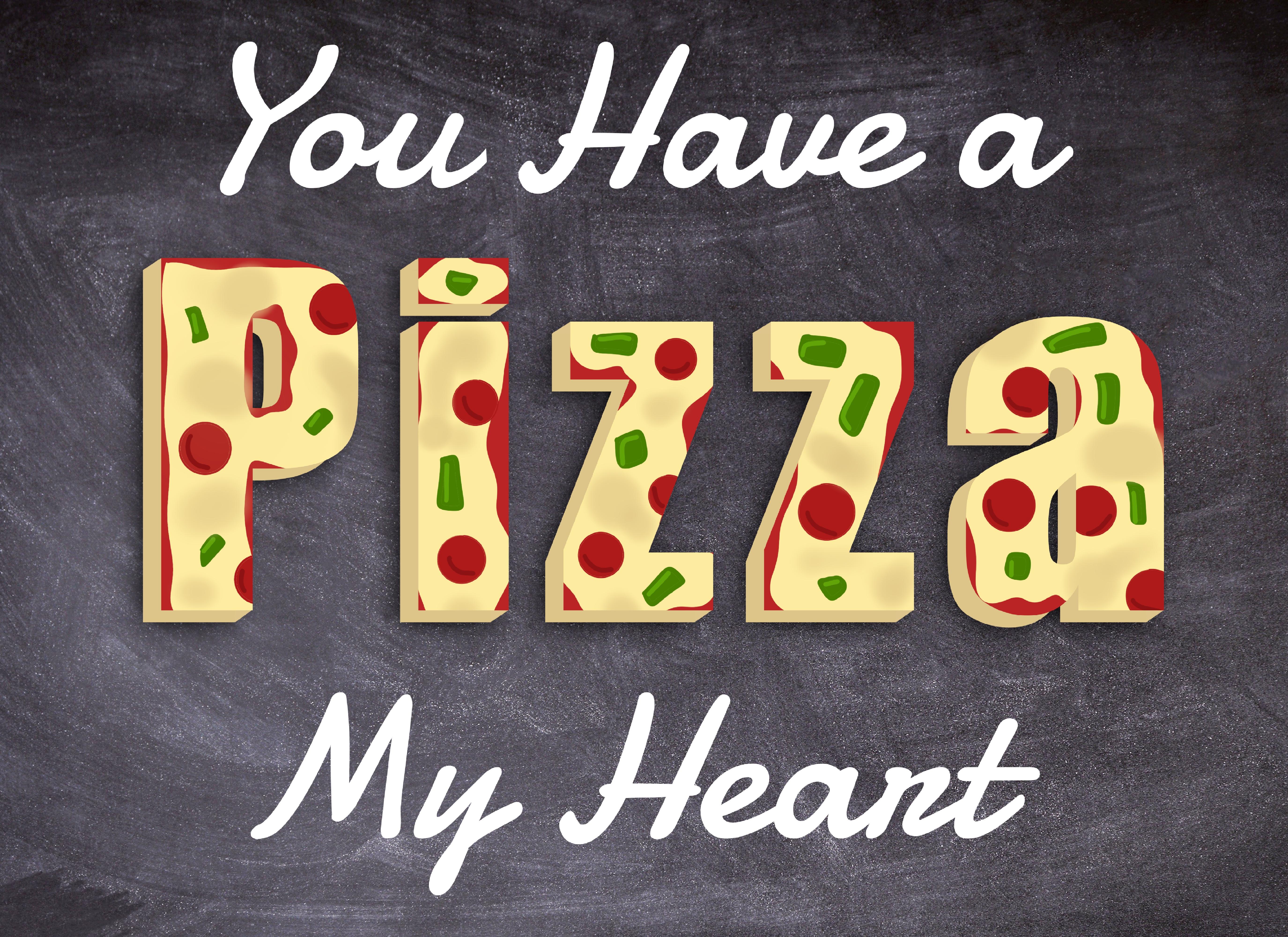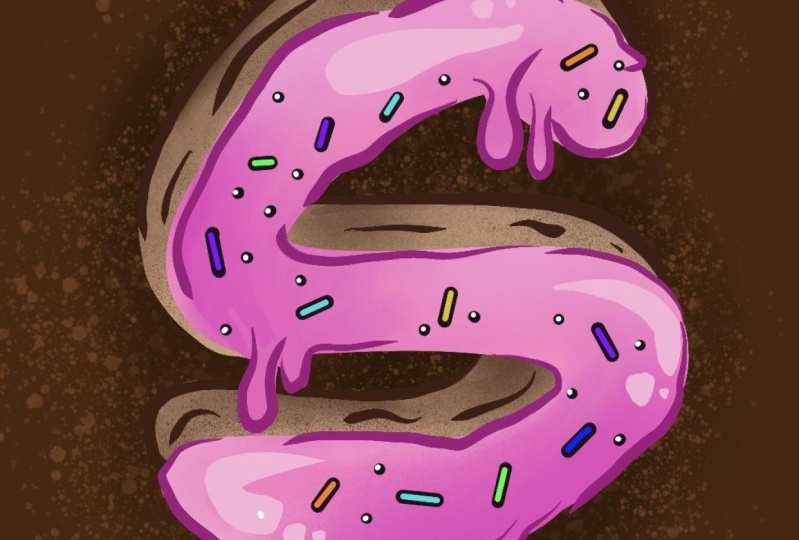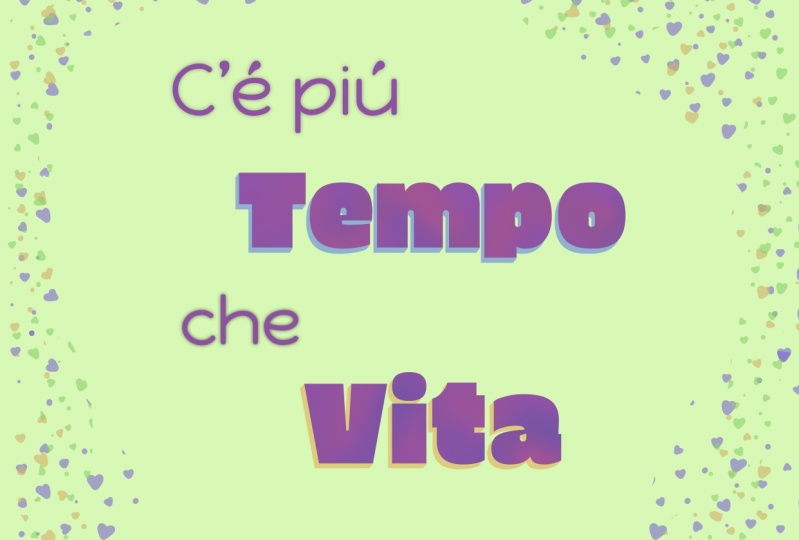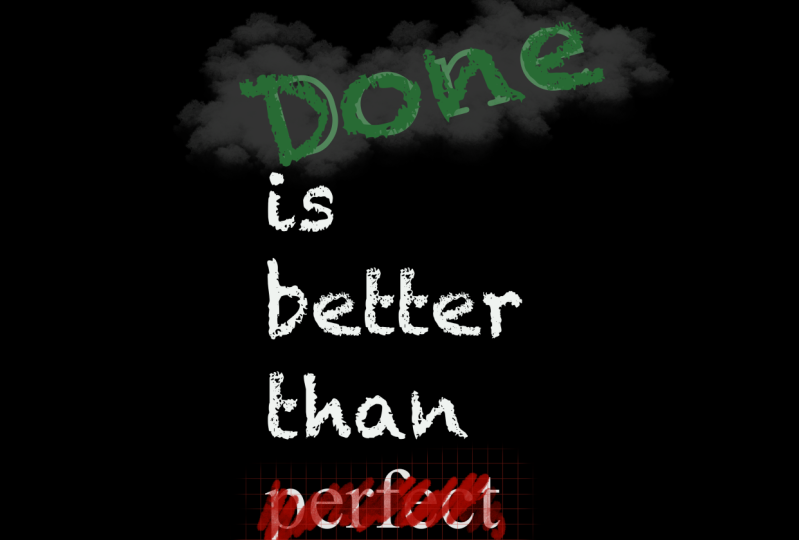
Level sua tipografia com escovas de criação | Danielle Brunner | Skillshare
Level sua tipografia com escovas de criação
Este curso combina o design gráfico com técnicas ilustrativas para aprimorar sua tipografia. Você vai aprender a usar escovas em texto para criar uma imagem dinâmica que pode ser usada em cartões de aniversário, cartazes/impressões de arte, posts de mídia social e muito mais! Não são necessárias habilidades de letras de mão!
E como bônus, você também vai aprender a criar sua própria escova de criação de criação. Esta aula é ótima para aqueles novos em Procreate, design e ilustração digital.
1. 1 classe de tipografia Introdução 10: Você já quis explorar mais do que apenas ilustrar e desenhar no Procreate no seu iPad? Bem, neste curso, eu vou te mostrar exatamente como fazer isso. Olá, meu nome é Danielle Burner. Sou designer gráfico e ilustrador de Pittsburgh, Pensilvânia. Neste curso, mostrarei as ferramentas e truques necessários para melhorar sua tipografia e procriar. Vamos criar um projeto divertido com tema de sobremesas. E depois de concluir sua arte, você pode usar o que aprendeu para criar seu próprio tema para digitar quatro pôsteres, cartões de aniversário, postagens nas redes sociais e muito mais. E, como bônus, mostrarei como criar o pincel para confeitos para doces que incluí para você neste curso. Vamos começar. 2. 2 recursos de downloads de recursos de introdução de recursos: Estou muito animada para começar esta aula focada em meus dois assuntos favoritos, arte e deserto. Mas antes de começarmos, você vai querer baixar os recursos que eu forneci para você na seção de projetos e recursos abaixo deste vídeo. Verifique se você está usando o site da Skillshare e não o aplicativo para acessar esses arquivos. Você fará o download do arquivo de topografia do deserto dos pincéis e do arquivo de cores da paleta do deserto. Ao clicar neles, sempre escolha a opção abrir e procriar. Em seguida, você encontrará o novo conjunto de pincéis na parte superior da sua biblioteca de pincéis e a paleta de cores será adicionada à sua biblioteca de amostras. Por fim, quero mostrar como acessar as duas fontes gratuitas que usaremos nesta aula. Acesse fonts.google.com, LinkedIn, a seção Sobre abaixo deste vídeo. Aqui, você pesquisará e baixará happy monkey e Erica, um. Se você quiser escolher seu próprio tipo de letra ou usar os que você já tem, certifique-se de usar duas opções de contraste. Um tipo de bloco san-serif mais espesso e outro com uma escrita ou um peso geral mais leve. Você pode usar as propriedades da fonte para restringir suas pesquisas em fonts.google.com. Agora que você tem todos os seus recursos, estamos prontos para começar a criar nossa tela. 3. 3 preparo e layout de fontes do Canvas: Nosso primeiro passo será criar nossa tela e preparar nossas fontes. Abra seu aplicativo Procreate e criaremos um novo Canvas. Então, você tocará no sinal de mais no canto superior direito. E vamos usar uma tela de 4.000 por 4.000 pixels. Isso é algo que eu já criei, mas se você não tiver isso em sua biblioteca anterior do Canvas, mas se você não tiver isso em sua biblioteca anterior do Canvas, toque neste sinal de adição aqui e verifique se ele está configurado para pixels. Você pode ver que aqui suas opções estão desse lado. Então, vamos digitar 4.000,4 mil. E você verá que se estivermos em 300 DPI ou as camadas máximas forem 29. Então, podemos ter 29 camadas nesta peça. Se você aumentar o tamanho , as camadas diminuirão. Então, preste atenção a isso quando estiver fazendo qualquer projeto. Toque em Criar e a tela em branco estará pronta para ser usada. Próximo. Vamos adicionar nossa cor de fundo. Então vá para o menu Camadas e selecione a cor de fundo. Com a paleta do deserto carregada. Vou selecionar esse tom azul escuro. Agora, vamos adicionar nosso texto. Vá até o ícone da chave inglesa, que é o menu Ações. Verifique se você selecionou adicionar e adicionar texto. Vamos começar com a palavra doce. Toque duas vezes e selecione a seleção da fonte. Já tomei Erica Won. Mas se você estiver em outra coisa, certifique-se de ir até Erica won ou bloquear o texto que você escolheu e clicar em Concluído. Selecione a seta para redimensionar. Você pode selecionar Snapping se quiser que ele fique exatamente no meio. E ele se encaixará no local que você deseja. Para torná-lo mais exato. Você verá que a Suíte foi adicionada à sua própria camada aqui. Vamos adicionar mais um pouco de texto. Então, primeiro vamos ter uma e eu quero mudar essa fonte para a fonte Happy Monkey que escolhemos. Está feito. Eu faço isso um pouco menor. Vou fazer doces ainda maiores. Centralize isso. E vamos adicionar a parte inferior, que vai dizer aniversário. Você pode selecionar todas as três camadas de textos certificando-se de que estejam todas selecionadas aqui, aniversário. E então vamos deslizar para a direita. Deslize para a direita novamente e você verá que todos os três estão destacados. Você pode ir até a seta e mover todas elas ao mesmo tempo depois de ter tudo configurado. Dessa forma, se você estiver ativada, você pode colocar tudo no centro. Ok, isso parece muito bom. Então, em seguida, vamos começar a desenhar para aprimorar a palavra doce e transformá-la em um deserto. 4. 4 dicas para adicionar profundidade: Em seguida, usaremos algumas habilidades de desenho para criar nossas próprias letras em bloco em 3D. Vamos começar aqui, certificando-nos de que nossas fontes são e da cor em que queremos que elas estejam. Os meus já estão prontos. Mas você verá que esse é o rosa escuro que eu escolhi como a cor da cobertura. Se você não estiver nessa cor, você pode tocar duas vezes na fonte que deseja alterar, para selecioná-la, tocar na sua cor e alterá-la. O que vamos fazer agora é garantir que a fonte doce seja selecionada. Deslize para a esquerda e duplique. Selecione a cor doce inferior e toque em. Vamos colocá-lo em restaurantes. Isso permitirá que você faça alterações na decoração, mas não poderá alterar o tipo. Portanto, certifique-se de que, depois de rasterizar, você já definiu a palavra como, você queria dizer. Agora vamos escolher o Alpha Lock. E você verá esse fundo quadriculado. É assim que você sabe que o Alpha Lock está ligado. Isso nos permitirá mudar apenas essa palavra, exatamente o que está selecionado aqui. Vamos escolher a cor do biscoito. Toque nessa camada inferior doce que está na camada de preenchimento de bloqueio alfa. E agora você pode ver que mudou para essa cor de dez biscoitos, o que é uma maneira muito fácil de fazer isso. Toque e retire-o do Alpha Lock. Você não deve mover a ferramenta e nós vamos mover isso. Na verdade, vou tirar a foto. E vamos apenas movê-lo um pouco para dar um efeito 3D. Estou movendo-o para baixo e para a esquerda um pouco. E agora estamos prontos para começar a preencher com nossas ferramentas de caneta. Quero que você acesse o menu Camadas e crie uma camada abaixo da camada Sweet. Então, você tocará nesse sinal de mais e ele o colocará automaticamente acima. Então, basta pegá-lo e arrastá-lo para baixo. Aqui. Vamos usar o conjunto de canetas para topografia do deserto. E vamos usar a caneta técnica porque ela é menor e mais fácil para detalhes finos. E certificando-se de que você está na nova camada abaixo. zoom e adicionaremos algumas linhas para criar letras em bloco. Então você vai querer desenhar. E se você segurar sua caneta verá que ela forma uma linha reta. E você deve preenchê-lo para poder colorir até o fim ou garantir que tenha uma forma sólida preenchendo os três lados. Você vai ver se tiramos isso e tiramos isso. Eu fiz um triângulo. É assim que você sabe que o preencheu. E então você pode usar a cor solta ao tocar e segurar e arrastar e soltar para preencher a camada. Alguns foram dados a você tão rapidamente. E até quando estiver trabalhando em algo que você quer tentar fazer é pegar sua camada de biscoito e os desenhos extras que você criou e deseja mesclar essas camadas. Você os aperta juntos. Ou você pode tocar um toque para a direita no outro. Isso seleciona os dois. Agrupe esse grupo, separe e nivelando. Então, essa é uma maneira mais longa de fazer isso, mas existem duas opções para você. 5. 5 Decoração e aprimoramento: Esta é minha parte favorita do projeto, em que decoramos nosso biscoito com, eu acho, redemoinhos e granulados para realmente dar vida a ele. Agora que temos nossa base de cookies totalmente configurada, vamos tirar algumas marcas de mordida dela. Vá até a borracha e, no conjunto de topografia do deserto, escolha monolina. Vamos nos certificar de que estamos na camada superior da suíte. Queremos rasterizar para que possamos fazer edições nessa camada com a borracha. Amplie até um ponto e vamos dar alguns toques que podem parecer dentes. Em seguida, você vai para a camada de cookies abaixo toque novamente na borracha. E então você pode simplesmente apagar. Agora, quero adicionar alguns elementos extras adicionando algumas migalhas para que a mordida foi retirada. Vá até suas camadas e crie uma nova camada acima tudo. Com seu pincel. Vamos escolher a monolina. E vamos usar a cobertura e as cores da sua paleta. Você pode ir em frente e apenas tocar em algumas migalhas. Como você achar melhor. Se você fizer algo que não queira fazer. toque com dois dedos será desfeito. E então, se você mudar de ideia, três dedos serão substituídos. Isso. Parece muito bom. Agora vamos ao nosso doce olá. Deslize para a esquerda, duplique. Toque na parte inferior, cadeado alfa. E vamos preenchê-lo com preto para obter preto puro, basta tocar duas vezes em qualquer lugar próximo ao preto e ele se encaixará na camada alfa bloqueada. E vamos preencher a camada. Toque novamente, desfaça o Alpha Lock. E vamos até essa varinha mágica, que é o menu de ajustes, e escolheremos o desfoque gaussiano. Aqui está o nosso tamanho. Deslizar para ajustar significa pegar sua caneta e simplesmente deslizar. Vou dar uma pequena sombra sobre isso e chegar a 13%. E volte para suas camadas. Toque neste n para ver algumas opções aqui. Vou diminuir um pouco a opacidade. Você pode ver como isso muda um pouco. Só queremos um pouco de sombra. Ok, agora estamos prontos para decorar. Vá até sua camada doce com a cobertura rosa e toque no botão Plus para criar uma nova camada acima dela. Toque novamente e agora vamos criar uma máscara de recorte. Isso garantirá que o que fazemos seja apenas nessa camada, mas em vez de colocar o bloqueio alfa diretamente na camada, ele está criando uma máscara acima dela para que não façamos as edições diretamente nessa camada. Vou escolher um rosa mais claro, talvez o próximo abaixo do escuro. Para o pincel, vou escolher o pincel macio. Vamos criar alguns redemoinhos de gelo. Gentilmente. Gire, não é exatamente o número oito, mas pense em cobrir um bolo, como você pode colocar a cobertura para criar alguma dimensão. Então você pode ver onde estamos lá. Você pode ficar ainda mais claro ou mais escuro. E, você sabe , ajuda adicionar um pouco de dimensão com alguns destaques, como esse. E isso cria um efeito que dá mais dimensão à nossa cobertura. Em seguida, quero criar outra máscara de recorte acima delas. Então, só vai ficar de joelhos. E eu quero colocar um pouco do meu granulado. Vou começar com essa cor dourada e amarelada. E eu vou escolher o avião Party Sprinkles. Tem um arco-íris e um normal. Então escolha o normal para isso. E vamos simplesmente exagerar. Agora eu também quero adicionar um pouco de roxo. E, novamente, da maneira que você quiser que sejam feitas, você pode adicionar ainda mais cores ou menos cores. Você pode tocar ou deslizar sua caneta. Agora, quero adicionar uma camada por baixo de tudo. Então vá para a camada inferior, toque e arraste-a até a parte inferior. Eu quero fazer algumas dessas borrifadas de arco-íris ao redor, quero por baixo. Então, caso não estejamos exagerando nossos textos. E com isso, isso é sensível à pressão. Estou empurrando e pegando e é direcional. Então, a cor mudará dependendo do que você está fazendo. Então, nós só queremos uma brincadeira divertida de fronteira com isso para fazer o que você quiser e achar que é bom. Depois de pegar seu lápis com este link, você pode ir por cima assim. Mas uma vez que você o pega e o coloca de volta no chão, ele vai colocá-lo em camadas. Então, fique atento a isso. Mas um pouco de aspersão. Dessa forma. É meio divertido. Você pode, você não precisa usar o arco-íris. Você pode escolher sua cor, mas eu gosto da espontaneidade do look do arco-íris. Agora você tem sua mensagem de aniversário completa. Enquanto esse projeto estiver pronto, assista ao próximo vídeo para receber um bônus, onde eu posso te ensinar como fazer esses pincéis para polvilhar doces e talvez aprimorá-los com suas próprias formas. Polvilha. 6. 6 BÔNUS Faça sua própria escova de salpicar de doces: Para a cereja no topo do bolo ou na cobertura do biscoito, trago esta pequena lição bônus de como fazer seu próprio pincel. As possibilidades são infinitas quando você pode criar seus próprios pincéis para usar no Procreate em todos os seus projetos futuros. Ok, vamos começar com um Canvas de dez por dez a 300 DPI. Eu escolhi preto sólido. Você vai querer ter certeza de fazer o mesmo. E eu vou usar o pincel monolina. Tudo o que vamos fazer é desenhar nossos granulados ou qualquer tipo de doce ou cobertura que você queira desenhar. Apenas um monte de direções diferentes. Ajude qualquer tamanho que você ache que possa parecer bom. Para tornar isso um pouco diferente do que já criamos, na verdade vou torná-lo um pouco maior. E você já viu aquelas bolinhas de doces que eles têm na seção polvilhada para assar. Adicione algumas dessas variações. Novamente, este é o seu pincel, então faça-o do tamanho que você deseja. Espaços. Depois de configurar seus padrões, quero que você deslize três dedos para baixo na tela copie tudo criando uma nova camada. É aqui que vamos testar nosso pincel. Vamos seguir em frente e voltar para sua biblioteca de pincéis. E certifique-se de que você está usando seu conjunto de pincéis para topografia do deserto e toque neste plus para criar um novo pincel. Dentro dessa biblioteca. Vamos escolher Granular, Editar, Importar, tocar ao lado para nos livrar desse menu. E, na verdade, você vai tocar com dois dedos para inverter o branco igual ao seu pincel. Seja o que for, branco é o que seus pincéis serão. Outra vez, você poderia realmente mantê-lo do outro jeito. E o coproprietário seria esse filme de fundo. Talvez haja algo que você crie que possa exigir um pincel como esse. Mas para este, queremos que seja o verdadeiro granulado ou o pincel. Então clique em Concluído. E você pode ver que é aqui que você pode testar seu padrão. Vamos acessar esse menu. Você verá que há muitas opções que eu sugiro à medida que você avança, basta jogar, jogar com todas essas opções para ver que você gosta ao começar a aprender a criar mais pincéis. Desative a instabilidade de compensação porque queremos que seja mais preciso. Este Zoom onde é cortado. Tire porque queremos que seja qual for o tamanho decidimos que será desse tamanho. Se estiver totalmente acima, não importa o tamanho que você fizer, sempre será aquele ajustado para esse tamanho ou para o maior tamanho. Eu quero que minha escala seja em torno de 35 é 36%. Para este pincel em particular. Em seguida, escolha Propriedades. Vamos dar uma olhada no comportamento do pincel. Para esse pincel em particular, quero aumentar o tamanho máximo. Nos anos 300. Alguma coisa. Essa visualização é a prévia que você vê na sua biblioteca de pincéis. Eu não quero que seja cerca 5% ou mais por cento feito. E você pode ver que isso é o que criamos. Você pode testar conforme necessário. Desfaça isso. Você sempre pode voltar e editar tocando em. Então, temos mais uma coisa a fazer aqui com o pincel real. Bom lápis Apple. Para o meu pincel, vou diminuir a opacidade para desligá-lo. Se você quiser que seja sensível à pressão , você pode mexer com isso, mas eu quero que seja sempre um granulado sólido. Então, vou desligar o meu. Em seguida, certifique-se de dar um nome a ele. Sobre este pincel, toque aqui onde diz Sem título. Vou dar um nome aos meus dançarinos e pronto. Aí está. Agora você pode escolher qualquer cor que tenha em seu paladar, sua cor favorita. E você pode adicionar isso conforme necessário. Para o seu projeto. Espero que você tenha gostado dessa aula bônus. Adoro fazer pincéis. Isso torna a vida muito mais fácil quando há algo que você deseja criar e que deseja criar repetidamente. Você pode fazer isso uma vez e sempre fazer isso. 7. 7 pensamentos finais: Bem, nós fizemos isso. Seu projeto finalizado deve ser mais ou menos assim. Ou talvez seja um pouco diferente se você decidir personalizá-lo. Agora você pode pegar essa arte e postar nas redes sociais para o aniversário de alguém. Ou talvez você queira colocá-lo em um cartão de aniversário e imprimi-lo para um amigo ou membro da família. Nesta aula, concentre-se novamente nas camadas e em como aplicar máscaras de recorte e bloqueio alfa. E a diferença entre como instalar fontes, paletas de cores e pincéis, bem como criar seu próprio pincel. Você pode usar essas ferramentas básicas e aplicá-las a todos os seus projetos daqui para frente. Para este projeto, não se esqueça de compartilhar os projetos abaixo para eu e todos no Skillshare para ver o que você está fazendo. Bem, eu me diverti muito desenhando com você hoje. Estou ansioso para ver todos vocês na próxima aula. Tão feliz fazendo arte.